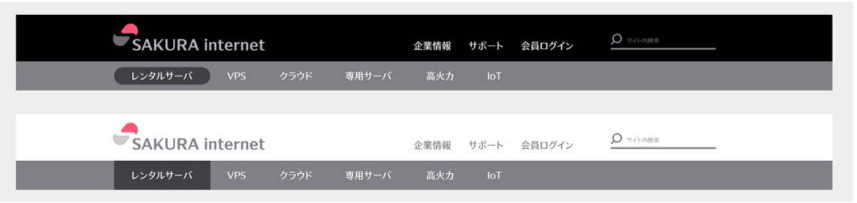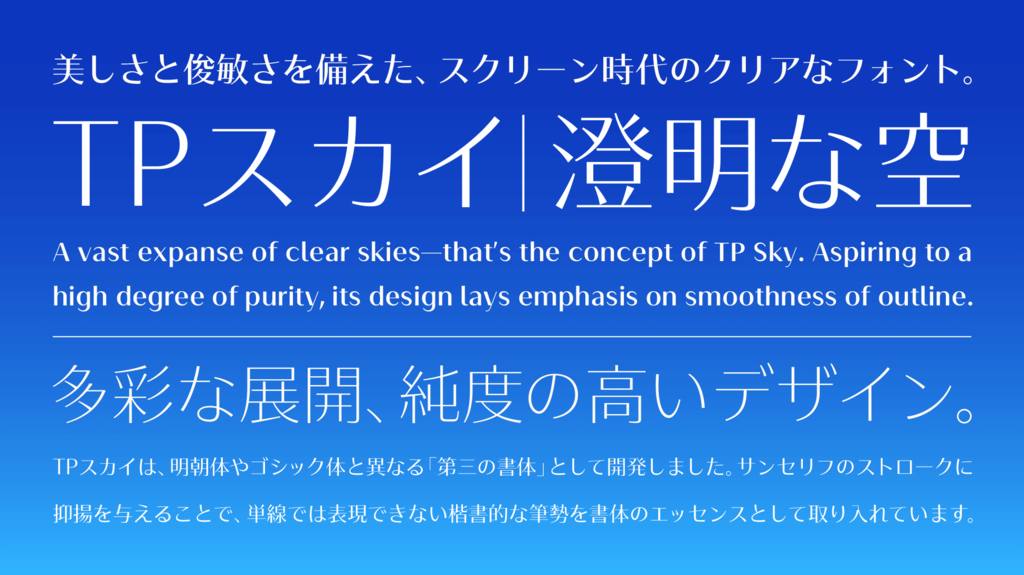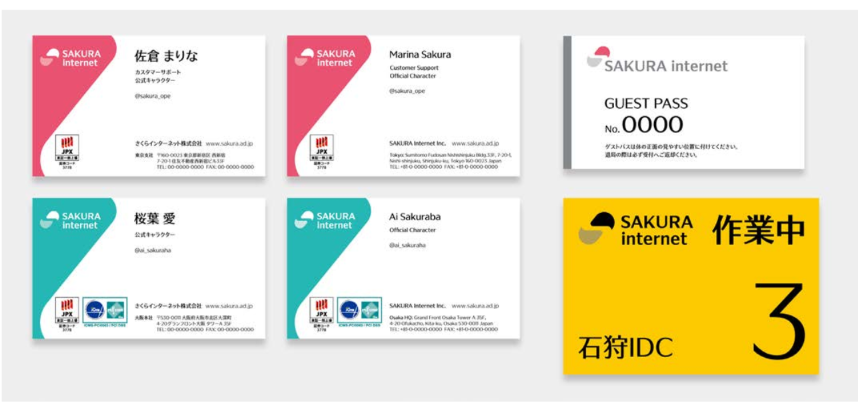
Haru TP
さくらインターネットがタイププロジェクトのフォント「TPスカイ」のカスタマイズ版「Haru TP」をコーポレートフォントとして導入したことを発表した。
▼TPスカイ
Haru TPの特徴
「Haru TP」は、創業20周年を迎えるにあたりロゴを一新したさくらインターネットの新ロゴデザインを担当した日本デザインセンターがそのロゴに合わせ、欧文書体164字を作成し「TPスカイ」の欧文の一部と入れ替えて収録。また仮名7文字のデザインも変更しており、こちらはさくらインターネットのロゴイメージに合わせた仮名として、新たにタイププロジェクトが提供している。
「Haru TP」は、ライト、レギュラー、ミディアム、ボールドの4ウエイトのファミリーで、名刺や社員証、カタログ、Webサイト、データセンターのサイン表示に使用される。
「リブランディングに際しては初期の段階から、Webや印刷物を独自のフォントをもちいて、社員のみなさん自身が運用することを構想していました。日本のウェブの黎明期から活動されていたさくらインターネット社にふさわしい、自律的なブランディングの方法論に感じたからです。そうした願いを込めて、桜が咲く季節である『Haru』という名前を提案しました。Haru TPの欧文はサンセリフ書体を基本としながら、緩急のついた日本的なシルエットを目指しています。このプロジェクトを、タイププロジェクトを含めた3社の共同で進められたことを、とても幸運に、そして光栄に思います」と、ロゴおよび欧文書体のデザインを担当した日本デザインセンターのオンスクリーン・デザイン研究所アートディレクター有馬トモユキ氏は述べている。
タイププロジェクトの鈴木功氏は「フィットフォントを基盤としたカスタマイズフォントを提供することは、タイププロジェクトの得意とするところです。今回は、発売したばかりのTPスカイをカスタマイズしてコーポレートフォントとして提供できたことをたいへん光栄に思っています。さくらインターネット社の『声』とも言えるHaru TPは、企業イメージに一貫性を与え、信頼性という資産の形成に役立つ事を確信しています」と述べている。